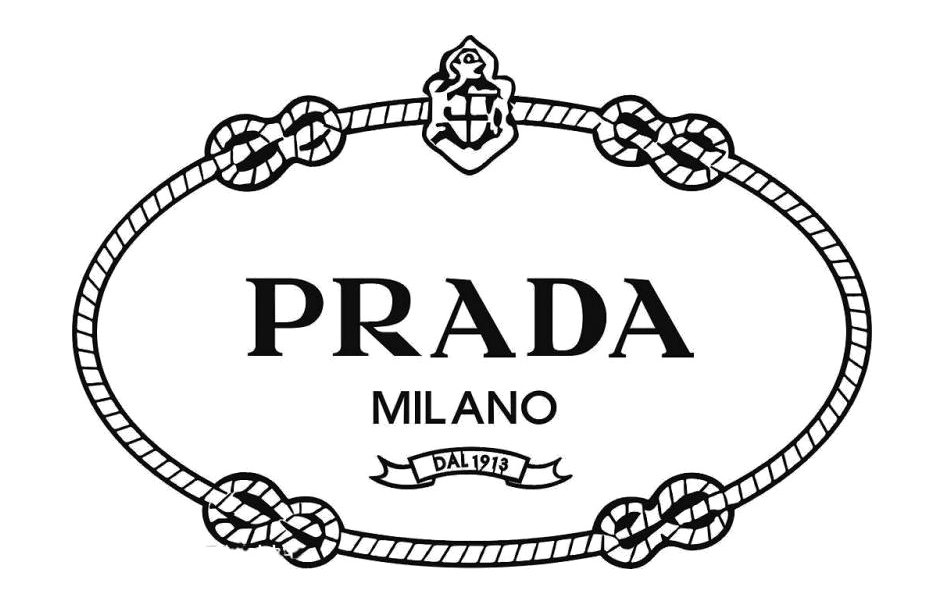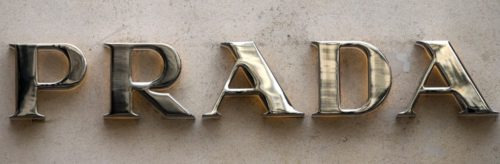
프라다 투명 로고 Prada Logo
프라다 로고의 역사는 1919년, 회사가 이탈리아 왕실의 공식 공급업체로 지정되면서 시작되었습니다.
이를 계기로 프라다는 로고에 사보이 왕가의 문장 요소를 사용할 수 있는 특별한 권한을 얻게 되었습니다.
프라다는 이 기회를 활용해 사보이 가문의 문장과 로프를 결합하여 첫 로고를 디자인했고,
여기에 프라다만의 독특한 워드마크를 더했습니다.
이탈리아 왕실의 공식 후원을 받았다는 사실은 같은 럭셔리 브랜드인 구찌와의 경쟁에서
프라다가 우위를 점하는 데 큰 도움이 되었습니다.
이처럼 왕실의 상징을 로고에 통합한 것은 브랜드의 가치를 높이는 탁월한 전략이었다고 평가받고 있습니다.
프라다 폰트
가장 초기의 프라다 엠블럼을 살펴보면 글꼴이 변경되지 않았다는 것을 알 수 있습니다.
현재 워드마크는 1919년에 도입된 로고와 동일한 맞춤형 세리프 올캡 글꼴을 특징으로 합니다.